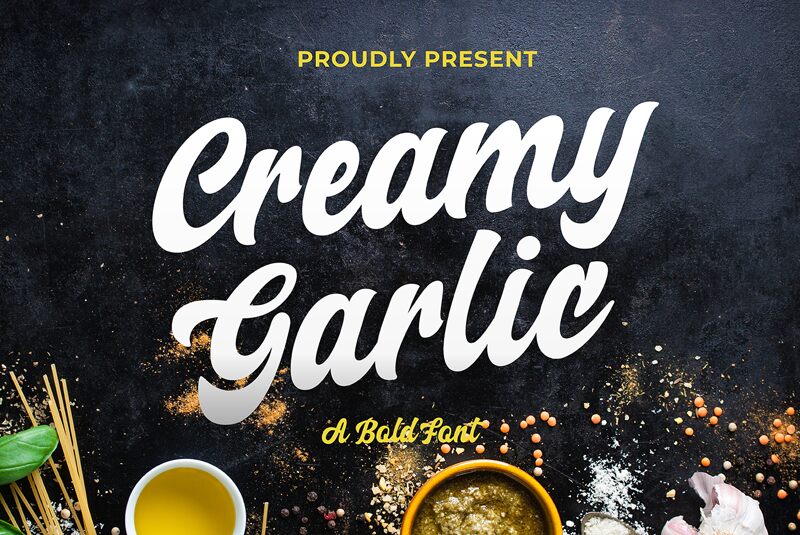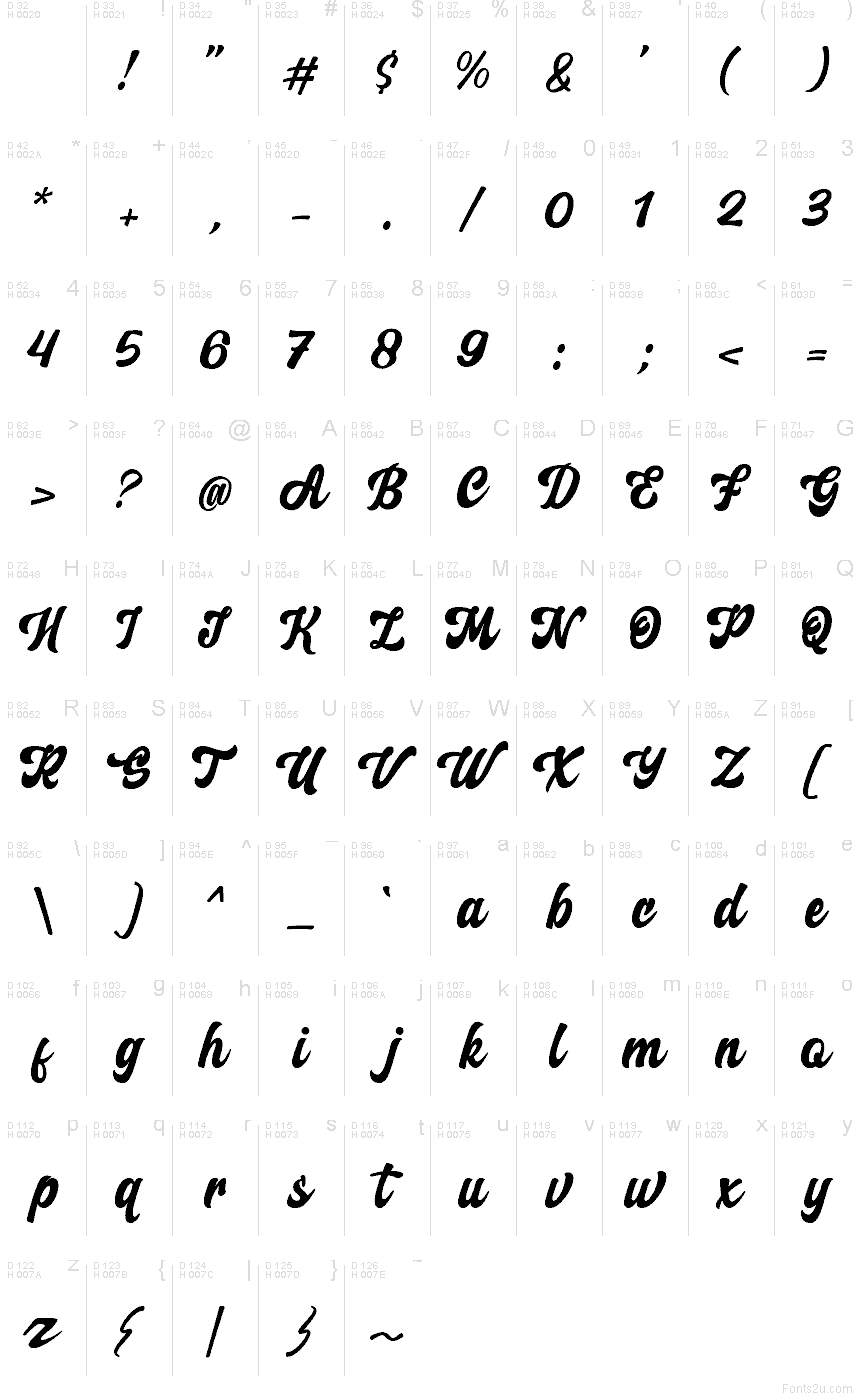
Creamy Garlic Script es una tipografía gratuita tipo pincel con un ritmo orgánico, pintado a mano y un toque retro muy dulce. Las letras se ensanchan y se afinan como los trazos de un pincel de rotulista, con uniones redondeadas y un flujo suave que mantiene el estilo cremoso y cálido, evitando durezas.
Es ideal para packaging, imagen de marca de cafeterías, menús, cartelería y gráficos para redes sociales donde busques una fuente gratuita que aporte calidez sin resultar recargada. Funciona especialmente bien en titulares cortos, logotipos o textos destacados, ya que sus trazos anchos y conectados dan a cualquier palabra una presencia llena y con mucha personalidad.
Creamy Garlic Script
Faras Dina